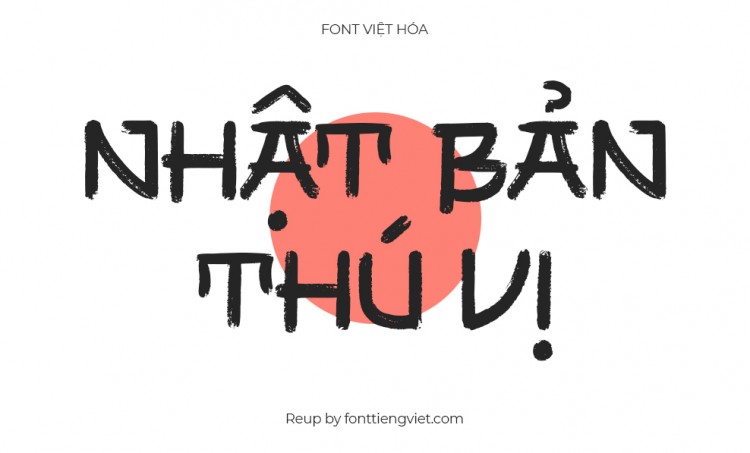
Font việt hóa SVN Shikamaru ( Phong cách nhật )
Font việt hóa SVN Shikamaru ( Phong cách nhật ) – Lựa chọn hoàn hảo cho thiết kế sáng tạo
Giới thiệu về Font việt hóa SVN Shikamaru ( Phong cách nhật )
Trong thế giới đồ họa hiện đại, việc tìm kiếm một bộ Font Miễn Phí mang đậm bản sắc văn hóa luôn là ưu tiên hàng đầu của các nhà thiết kế. Font việt hóa SVN Shikamaru ( Phong cách nhật ) là một tác phẩm nghệ thuật chữ viết độc đáo, lấy cảm hứng từ những nét bút thư pháp mạnh mẽ nhưng không kém phần uyển chuyển của xứ sở hoa anh đào. Bộ font này không chỉ mang lại vẻ đẹp thẩm mỹ cao mà còn giúp người dùng truyền tải linh hồn của văn hóa phương Đông vào từng sản phẩm thiết kế một cách tinh tế và chuyên nghiệp nhất.
Đặc điểm nổi bật của bộ Font việt hóa SVN Shikamaru ( Phong cách nhật )
Phong cách thiết kế độc bản
Đúng như tên gọi, Font việt hóa SVN Shikamaru ( Phong cách nhật ) sở hữu những đường nét gãy gọn, mô phỏng lại cách đi bút đặc trưng của nghệ thuật Shodo. Các ký tự được chăm chút tỉ mỉ, tạo nên sự cân bằng giữa tính hiện đại và truyền thống. Đây là lựa chọn lý tưởng cho các dự án liên quan đến manga, ẩm thực Nhật Bản hoặc các poster phim hành động cần sự bùng nổ về thị giác.
Khả năng ứng dụng linh hoạt
Mẫu font này đã được tối ưu hóa tiếng Việt hoàn chỉnh, giúp các bạn học sinh và giáo viên dễ dàng sử dụng trong việc thiết kế slide bài giảng, báo tường hay các ấn phẩm truyền thông trường học. Nhờ bảng mã chuẩn, font hoạt động mượt mà trên nhiều phần mềm thiết kế phổ biến hiện nay.